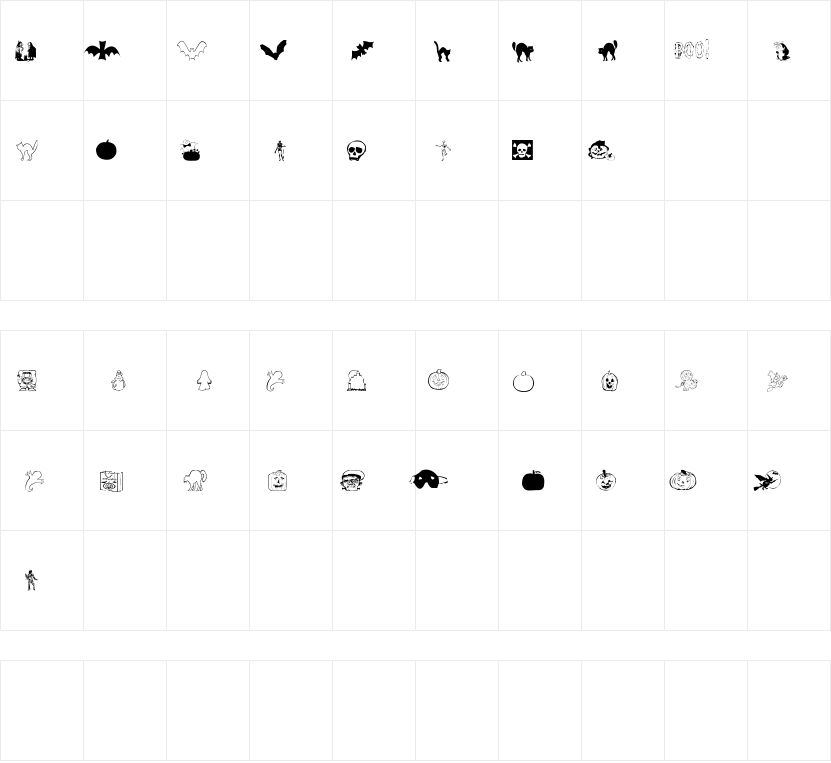
AEZ Halloween dingbats字体是一种专门为万圣节所设计的字体,它包含了各种与万圣节相关的图案和符号,例如南瓜灯、鬼魂、巫婆、墓碑等等。这种字体采用了手写风格的设计,看起来十分有趣和生动。AEZ Halloween dingbats字体可以应用于各种场合,例如节日海报、万圣节派对邀请卡、网站设计、卡片制作等等,可以为你的设计和文本增添一份神秘感和欢乐感。文件名:AEZ-halloween-dingbats-1.ttf
AEZ Halloween dingbats是一款非常不错的手写艺术字体,具有很好的视觉感,适合于文化类的宣传设计、商业类品牌的广告和产品包装设计以及个性化文字排版等较多场景。